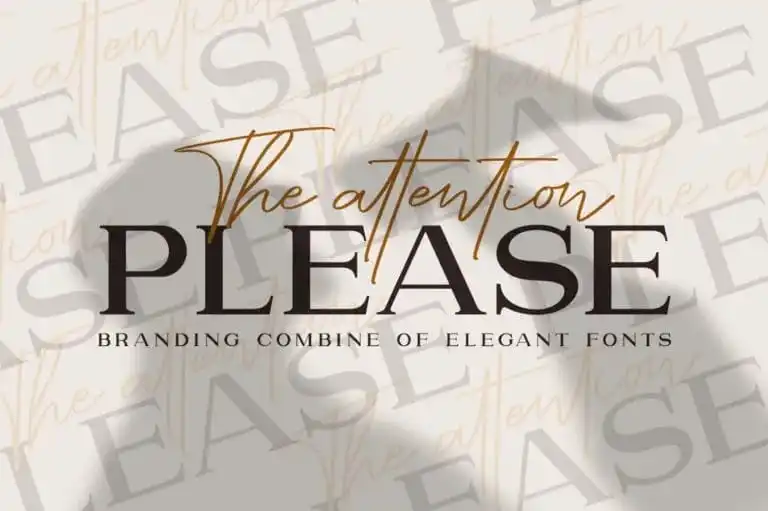
Please Serif Font – Fonte Grátis
Please Serif Font
A Please Serif Font é uma tipografia neo-grottesca baseada em formas geométricas, projetada para capturar a emoção contemporânea e amigável dos desenhos digitais modernos. Esta fonte idealmente se destina a ambientes de propaganda, marca, logotipo, embalagens, títulos e cabeçalhos, bem como design editorial. Ela é especialmente adequada para textos em maiúsculas, uma característica que torna a Please Serif Font perfeita para criar composições assertivas e memoráveis. Com muitas combinações de letras criadas ao longo da criação desta fonte, ela se destaca como uma escolha poderosa para qualquer aplicação visual. Seja em um layout editorial profissional ou uma campanha publicitária agressiva, a Please Serif Font é sua aliada perfeita para criar textos que chamam atenção e comunicam seu valor de maneira eficaz. Engajante e moderna, esta fonte atinge tudo o que você precisa em um único toque.